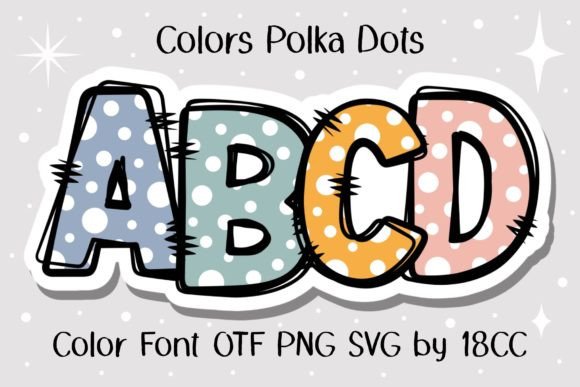
Colors Polka Dots Font
Colors Polka Dots Font – لمسة من الأناقة والمرح لتصاميمك!
أضف لمسة فريدة من الإبداع إلى مشاريعك مع خط Colors Polka Dots! يتميز هذا الخط بتصميم مرح مليء بالنقاط الملونة، مما يجعله مثالياً للاستخدام في التصاميم الجرافيكية، الشعارات، الدعوات، البطاقات، المنتجات الرقمية، والمطبوعات الإبداعية.
لماذا تختار Colors Polka Dots Font؟
✅ تصميم جذاب ومبتكر يضفي طابعاً حيوياً على أي مشروع
اجعل تصاميمك تنبض بالحياة مع Colors Polka Dots Font – الخيار المثالي لمن يبحث عن التميز والإبداع! ????????